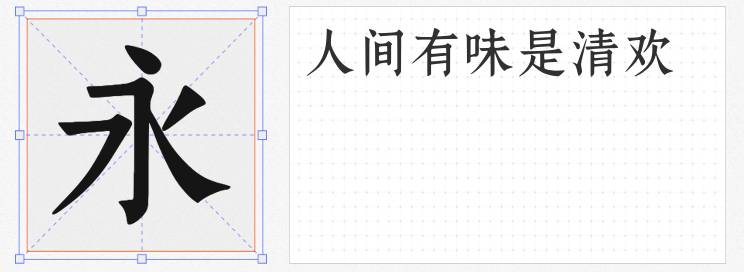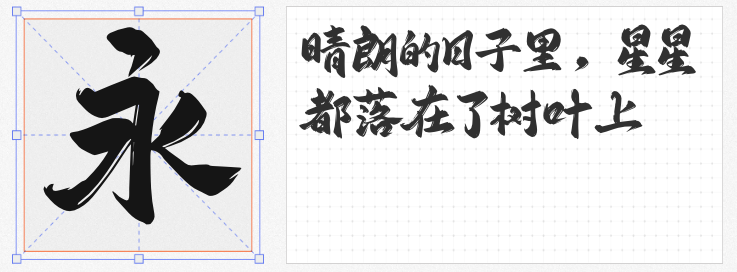
在国潮复兴的浪潮中,兼具文化底蕴与现代审美的字体设计成为品牌破圈的关键。本文精选四款免费商用字体,助您轻松打造高辨识度国风视觉作品。
1. 字库江湖古风体
这款字体以青铜器铭文为灵感,粗壮笔划传递出历史厚重感,而圆角转折设计则巧妙中和了传统书法的肃穆。特别适合作为标题字体,在茶饮包装、文创产品等场景中,既能彰显文化深度,又符合Z世代对"国潮不古板"的审美期待。其多层次笔划细节,在放大展示时能呈现类似浮雕的立体效果。
2. 鼎猎宋刻体
源自宋代雕版印刷的基因,经过数字化重构后,这款字体在保留刀刻纹理的同时优化了屏幕显示效果。其独特的"呼吸感"排版特性,使长文本呈现如古籍般的雅致韵律。特别推荐用于餐饮菜单、艺术展览手册等需要营造沉浸式氛围的场景,搭配宣纸背景可瞬间唤醒东方美学记忆。
3. 字库星球飞扬体
由AI辅助设计的这款字体,突破了传统书法字体的程式化局限。飞白笔触与连笔设计充满动态韵律,在运动品牌海报、音乐节视觉系统中能瞬间点燃热情。其智能适配系统支持多语言字符,满足全球化品牌的中英双语排版需求。
4. 阿里妈妈刀隶体
以爨宝子碑为蓝本,通过机器学习强化了三角点折的视觉张力。这款介于隶楷之间的实验性字体,在美妆包装、电竞海报等年轻化场景中展现出惊人的表现力。其打破均衡的结构设计,恰似当代青年文化中"不完美美学"的视觉诠释。